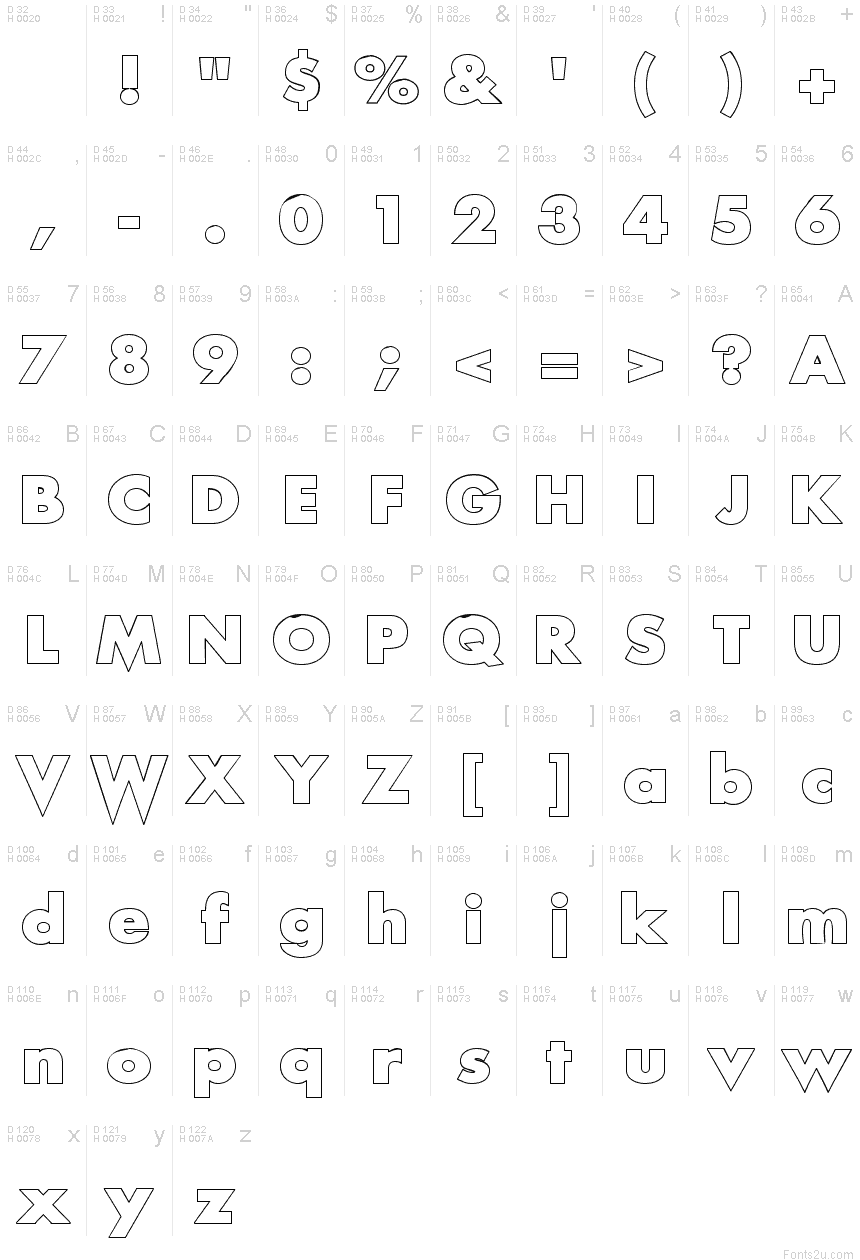
Scream Alternative Outlined von Samuel Park ist eine kostenlose, konturierte Horror-Display-Schrift, die vom Logo der Scream-Filme inspiriert ist. Die Buchstaben wirken eher weich und voluminös als scharfkantig, mit dicken, blasenartigen Konturen und einer unheimlichen Ruhe, die eher an Film-Branding erinnert als an Splatter.
Damit ist sie die perfekte Wahl für Filmposter, VHS-Cover, Halloween-Designs, Horror-Zines und Streaming-Titel. Überall dort, wo ein kostenloser Font mit dem ikonischen Slasher-Vibe schnell für Wirkung sorgen soll, ist diese Schrift ideal. Sie funktioniert auch hervorragend für kurze Logos und Monogramme, da die breiten, abgerundeten Formen selbst bei der Kontur-Variante gut lesbar bleiben und den Vibe der Thriller aus den 90ern perfekt einfangen.
Based on the Scream films logo. Samuel Park -99